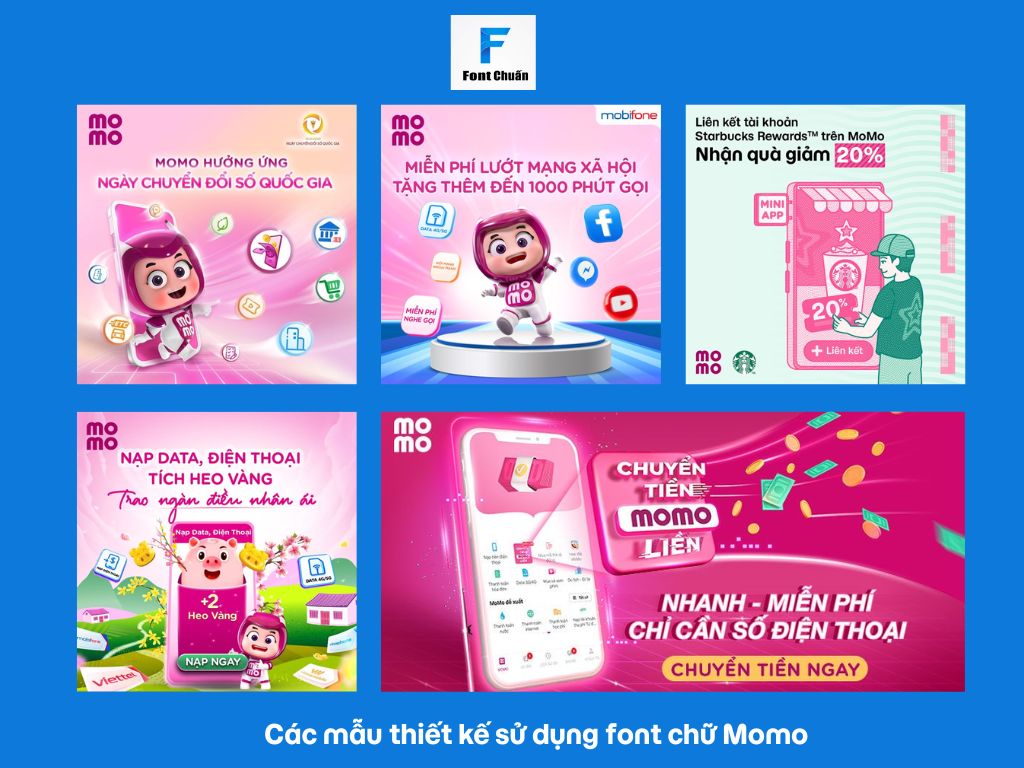
[Tải ngay] Bộ font MoMo – Kiểu chữ bo tròn hiện đại chuẩn thương hiệu
Font chữ MoMo là lựa chọn hoàn hảo cho những ai yêu thích style bo tròn, trẻ trung và hiện đại. Bộ font mang đậm tinh thần thương hiệu MoMo: thân thiện, dễ đọc và nổi bật trên mọi thiết kế. Nếu bạn đang tìm một kiểu chữ vừa đẹp mắt vừa hỗ trợ tiếng Việt đầy đủ, Font MoMo chính là lựa chọn lý tưởng.
Font chữ của MoMo là gì?
Font MoMo là một kiểu chữ mang phong cách dễ thương, bo tròn và hiện đại, lấy cảm hứng từ phong cách thương hiệu của ví điện tử MoMo. Bộ font này sở hữu những đường nét mềm mại, thân thiện, phù hợp với các thiết kế hướng đến sự trẻ trung, vui tươi và gần gũi.
Điểm đặc trưng của font chữ MoMo nằm ở độ cong tròn đều, tạo cảm giác thân thiện và dễ đọc dù hiển thị trên màn hình lớn hay thiết bị di động. Nhờ phong cách tối giản nhưng nổi bật, font MoMo được sử dụng rộng rãi trong các sản phẩm thiết kế như: poster, banner quảng cáo, infographic, video edit, card visit, hay các nội dung mạng xã hội.
Không chỉ đẹp và dễ tạo font chữ đẹp, font chữ của MoMo còn hỗ trợ đầy đủ tiếng Việt, đảm bảo không gặp lỗi ký tự khi dùng trong tài liệu, ấn phẩm truyền thông hay bài đăng mạng xã hội. Điều này giúp designer và editor thoải mái sáng tạo mà không cần chỉnh sửa nhiều, tiết kiệm thời gian nhưng vẫn giữ được tính thẩm mỹ cao.
Nếu bạn đang tìm những kiểu chữ chuẩn thương hiệu MoMo để dùng cho thiết kế, bài viết hay dự án sáng tạo, thì danh sách các font MoMo mới nhất dưới đây sẽ giúp bạn có mọi thứ cần thiết.
Font MoMo Trust Display
MoMo Trust Display là kiểu chữ được thiết kế riêng để sử dụng trong các tiêu đề, headline và hạng mục nổi bật của hệ thống nhận diện thương hiệu MoMo. Font này được phát triển dựa trên cảm hứng từ logo MoMo với các đường nét bo tròn, mềm mại, tạo cảm giác thân thiện, tích cực và gần gũi. Đây cũng là font mang tính “đại diện” nhất cho tính cách thương hiệu MoMo.
MoMo Trust Display chỉ có một độ dày (weight) duy nhất, điều này giúp giữ sự nhất quán trong mọi nội dung tiêu đề. Điểm mạnh của font chữ Momo nằm ở khả năng thu hút sự chú ý mà không gây rối mắt, rất phù hợp cho banner, poster, key visual hoặc tiêu đề trên website.
Khi sử dụng, font được khuyến nghị đi kèm các quy tắc về giãn dòng và kerning theo chuẩn brandbook để đảm bảo tính đồng bộ và tối ưu khả năng hiển thị.
Font MoMo Trust Sans
MoMo Trust Sans là font chữ được thiết kế để dùng cho nội dung thân bài, đoạn văn dài, caption, mô tả hoặc text nhỏ trong giao diện ứng dụng. Font giữ trọn phong cách bo tròn đặc trưng của font chữ MoMo nhưng tiết chế lại độ “cute” để tăng khả năng đọc trong các đoạn văn bản liên tục.
Font này bao gồm 3 độ dày: Light – Regular – Medium. Nhờ đó, người dùng có thể chọn độ dày phù hợp với từng ngữ cảnh mà vẫn duy trì được sự đồng nhất với hệ thống nhận diện MoMo. Trust Sans có khả năng hiển thị tốt ở nhiều kích thước, đặc biệt là trên nền tảng kỹ thuật số – nơi MoMo hoạt động mạnh mẽ nhất.
Khoảng cách dòng và ký tự của font cũng đã được chuẩn hóa theo hệ thống nhận diện, giúp văn bản đọc thoáng, rõ ràng và không bị rối mắt. Đây là font nên ưu tiên cho mọi phần nội dung dài từ 10 từ trở lên.
Font chữ MoMo Signature
MoMo Signature là kiểu chữ viết tay (handwritten) mang phong cách cá nhân, được sử dụng như một điểm nhấn đặc biệt trong thiết kế thương hiệu MoMo. Font mô phỏng nét viết mềm mại và tự nhiên của bút Script, giúp truyền tải cảm giác thân thuộc, ấm áp và giàu cảm xúc.
Font Signature thường được dùng để làm nổi bật các từ khóa quan trọng, hoặc nhấn mạnh cảm xúc trong tiêu đề khi đi kèm với MoMo Trust Display.
Font chỉ có một độ dày, vì vậy được khuyến nghị sử dụng tiết chế để tránh giảm tính chuyên nghiệp hoặc gây rối thị giác.  MoMo Signature không dành cho nội dung dài mà phù hợp nhất trong các tình huống như: chữ nhấn, slogan ngắn, từ tạo cảm xúc, hoặc các yếu tố highlight trong thiết kế.
Ứng dụng Font MoMo trong thiết kế
Mỗi font đảm nhiệm một vai trò riêng, giúp hệ thống nhận diện MoMo luôn đồng bộ, hiện đại và dễ đọc trên mọi nền tảng. Khi áp dụng vào thiết kế, cần hiểu rõ cách sử dụng từng font để tối ưu hiệu quả thị giác.
Dùng MoMo Trust Display cho tiêu đề
MoMo Trust Display được sử dụng dành riêng cho headline, các tiêu đề lớn hoặc nội dung cần thu hút sự chú ý. Kiểu chữ bo tròn, nổi bật giúp truyền tải sự thân thiện đúng tinh thần thương hiệu MoMo. Font chữ Momo này phù hợp trên poster, banner, trang chủ website hoặc các key visual quảng cáo. Tuy nhiên, chỉ nên dùng cho tiêu đề ngắn (khoảng 3–10 từ) để giữ sự cân đối và dễ nhìn.